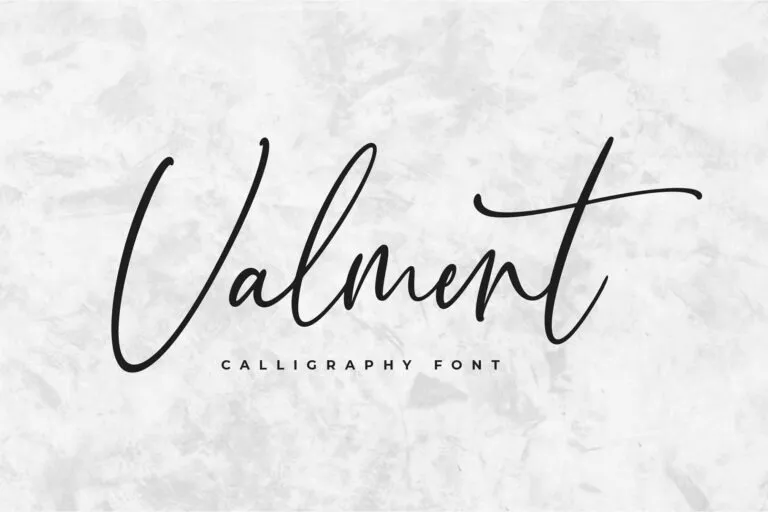
Valment Font – Download Grátis
A ‘Valment Font’ é uma elegante tipografia escrita a mão que foi criada por Pen Culture com um estilo script autêntico e casual. Esta fonte vem acompanhada de 72 belas ligaturas, tornando-a perfeita para novos projetos design. Suas características levarão seu trabalho a um novo nível, especialmente quando você começa a usá-la em aplicações como branding, logomarca, letra, logotipo, roupas, painéis de propaganda, revistas, embalagens, materiais de eventos especiais e muito mais. Uma escolha inteligente para estilos criativos ou elegantes em diversas áreas da design gráfico, a ‘Valment Font’ é uma excelente adição ao seu arsenal de fontes.